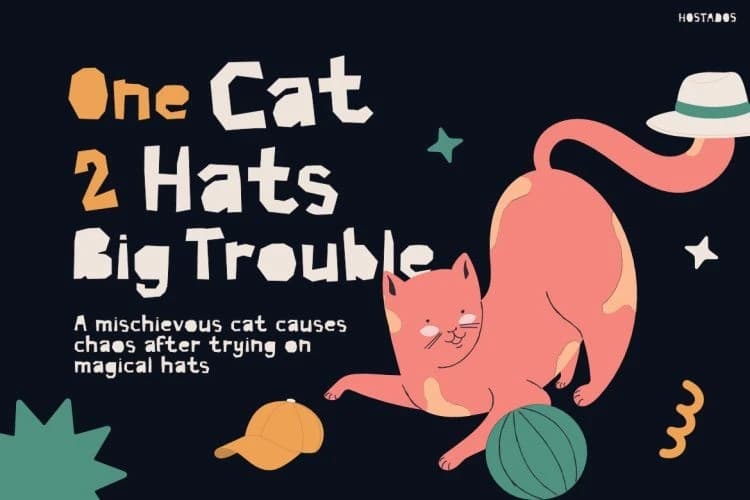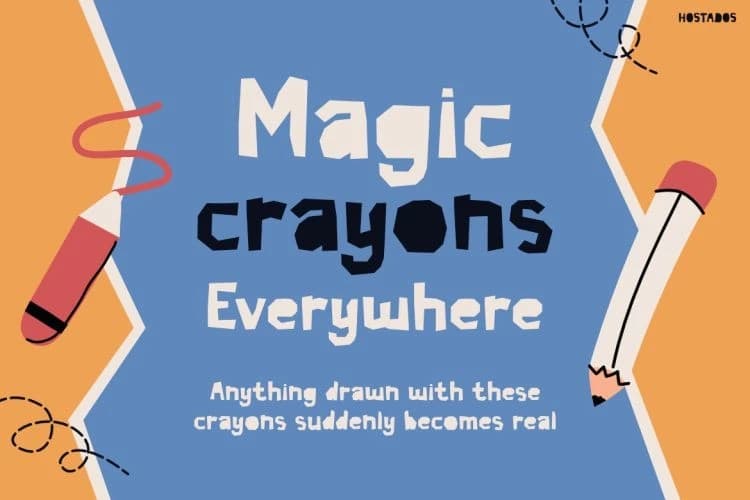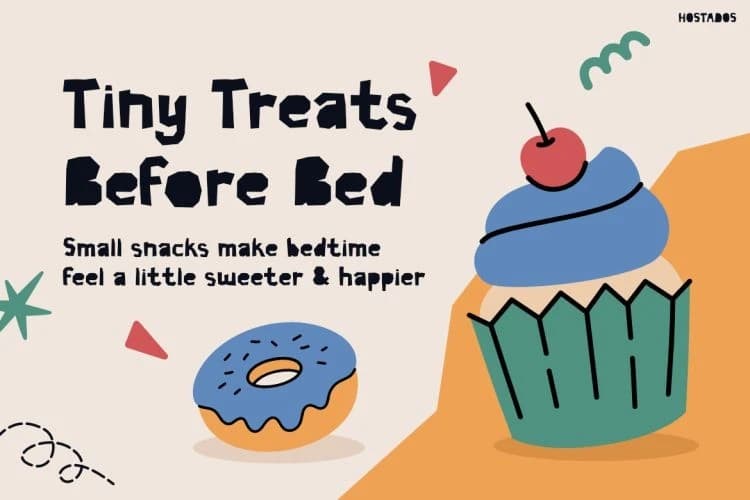
Hostados Gösterim Yazı Tipi
Hostados Display Font, her tasarıma neşeli enerji ve çocukça hayal gücünü katmak amacıyla yaratılmış eğlenceli ve tuhaf bir gösterim yazı tipidir. Öykü kitaplarından, karalama çizimlerinden, oyunbaz maceralardan ve renkli sınıf yaratıcılığından ilham alır.
Hostados Display Font, her tasarıma neşeli enerji ve çocukça hayal gücünü katmak için tasarlanmış eğlenceli ve tuhaf bir gösterim yazı tipidir. Hikaye kitaplarından, karalamalardan, eğlenceli maceralardan ve renkli sınıf yaratıcılığından ilham alınmıştır.